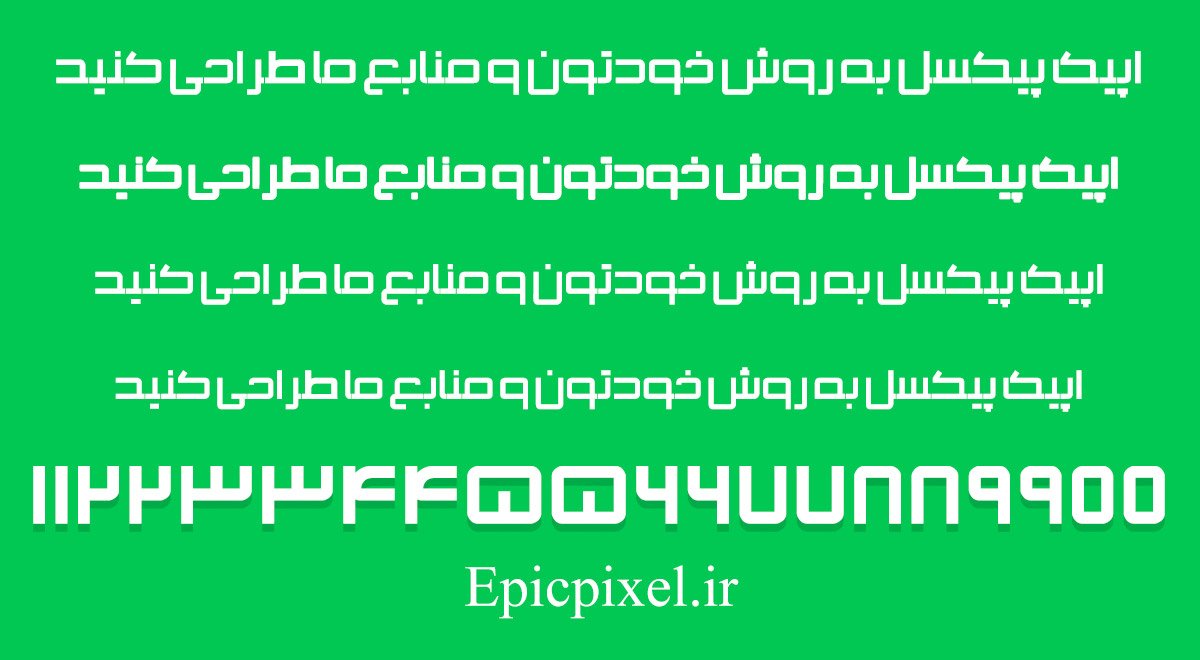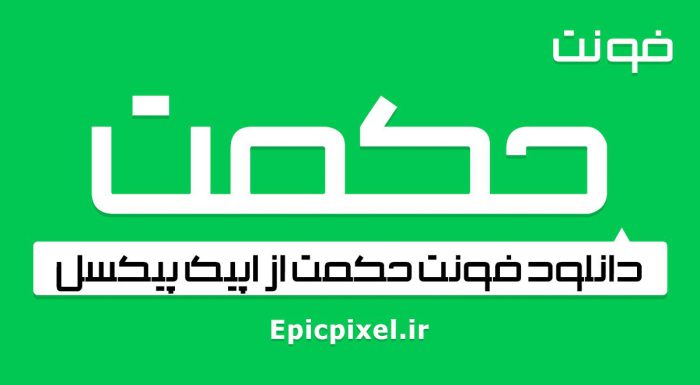
4 فونت حکمت فارسی
فونت حکمت فارسی با طراحی زیبا و خوانایی بالا، انتخابی ایده آل برای انواع پروژه های گرافیکی و متنی است که به دنبال ظاهری رسمی، کلاسیک و در عین حال مدرن هستند. این فونت با پشتیبانی از حروف فارسی و عربی، قابلیت های گسترده ای را برای طراحان و نویسندگان فراهم می کند و با بسیاری از نرم افزارهای طراحی و ویرایش متن سازگاری دارد.
ویژگی های برجسته فونت حکمت فارسی عبارتند از: طراحی حرفه ای و اصیل، تنوع در سبک های مختلف، خوانایی بالا در اندازه های کوچک و بزرگ، پشتیبانی از زبان های فارسی و عربی، و سازگاری با انواع سیستم عامل ها.
خیلی فونت چهارچوبی و اتوکشیده و با خط های منظم هست من لذت بردم برای کارهای فتوگرافی ام استفاده کردم و راضی هستم ممنونم